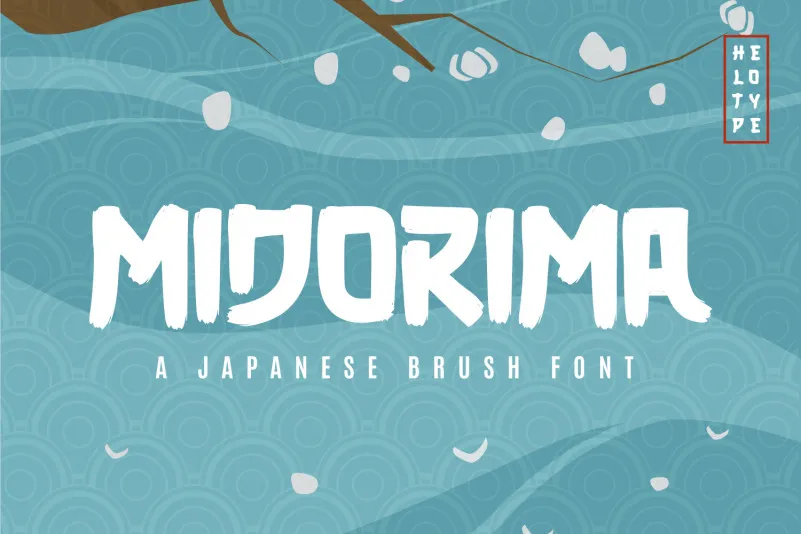
Aqui está uma descrição para a página de download da fonte Midorima Font: O design japonês deslumbrante de Midorima é perfeito para os ambientes culinários ou publicitários, proporcionando um ar sofisticado e elegante. Sua aparência brilhante e suavizada se adequa a menus de alimentos e anúncios de flyers com facilidade. Esta fonte atende aos requisitos do seu projeto, oferecendo inúmeras possibilidades para explorar suas potencialidades criativas. Engane-se ao pensar apenas em uso em menus: Midorima também traz um toque sofisticado a qualquer design gráfico que seja impresso ou exposto publicamente. Seja você um designer de ambientes culinários, publicitário ou mesmo de arte digital, Midorima é uma escolha inteligente para quem busca adicionar o sabor da cultura japonesa às suas criações visuais.